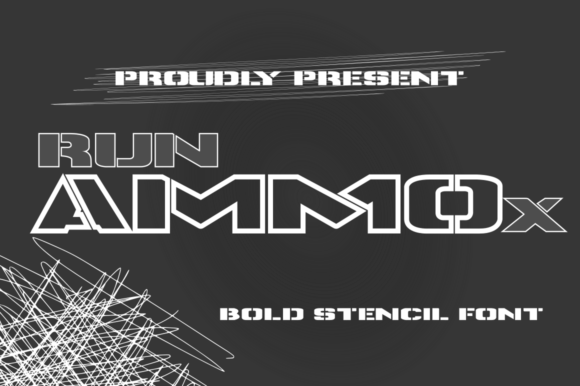
Runammox - это жирный трафаретный шрифт на плите.
Он добавит особый штрих к вашему дизайну.
Добавьте этот красивый шрифт к каждой вашей творческой идее и заметьте, как он выделяет их!